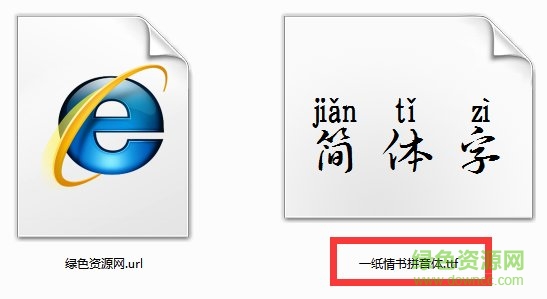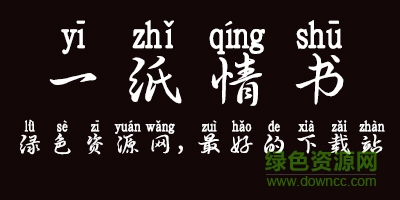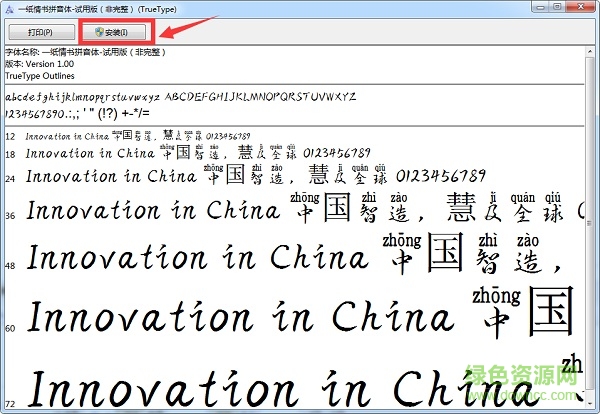
一紙情書拼音體ttf是一個免費的拼音字體。這款字體外形相當美觀,有點形似于行楷字體。字體可以用來設計海報、廣告等。喜歡這款字體的用戶快來綠色資源網(wǎng)下載使用吧。
一紙情書字體字體非常溫柔,書寫連貫,雖然沒有太復雜的筆畫,但是卻暗藏著內心的愛意。一紙情書拼音體,字體上沒有差別,依然保留了字體的溫柔一面!
1、溫柔似水,濃情蜜蜜;
2、辨識度高,使用廣泛;
3、筆畫不粗不細,恰到好處,可以用于正文編輯;
4、手寫風格,帶有連筆,書寫連貫流暢;
5、每個文字都會自動添加拼音。